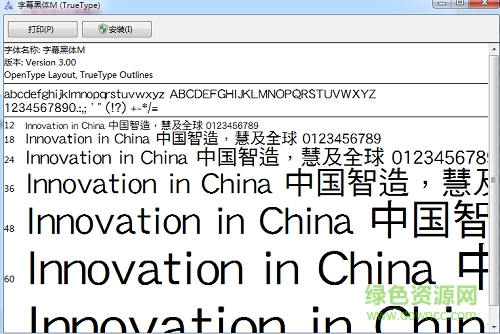
字幕黑體m字體是一款常規(guī)的黑體字體,纖細(xì)的字形但是又有黑體的醒目感,適合用在各種字幕中,感興趣的朋友趕緊來綠色資源網(wǎng)免費下載吧!
字幕黑體m是一款常用語字幕的黑體字體,它與黑體結(jié)構(gòu)相同,但點畫粗壯且粗細(xì)一律,起止皆方,氣象豐滿。字體空間的分配,色彩度的感應(yīng)變化及字體視覺真實與假象的運用,讓這款字體都與眾不同!